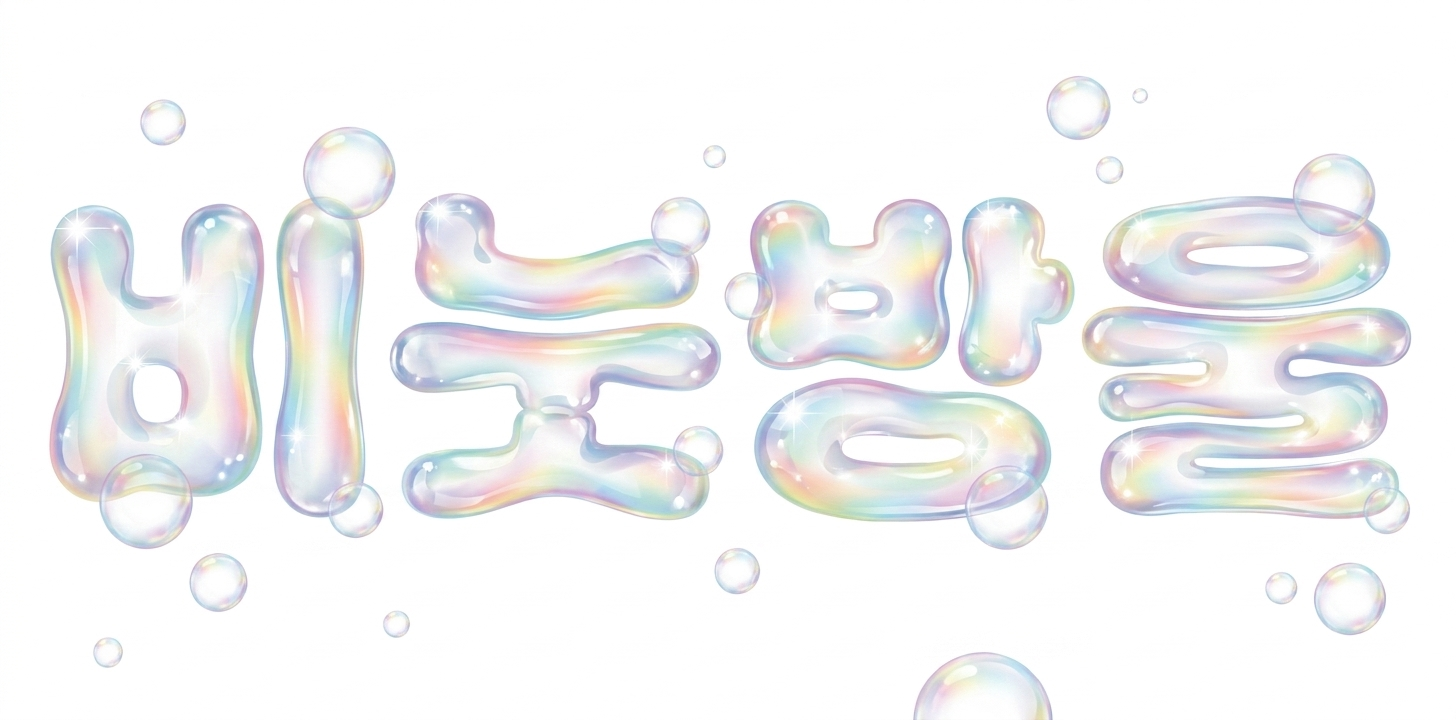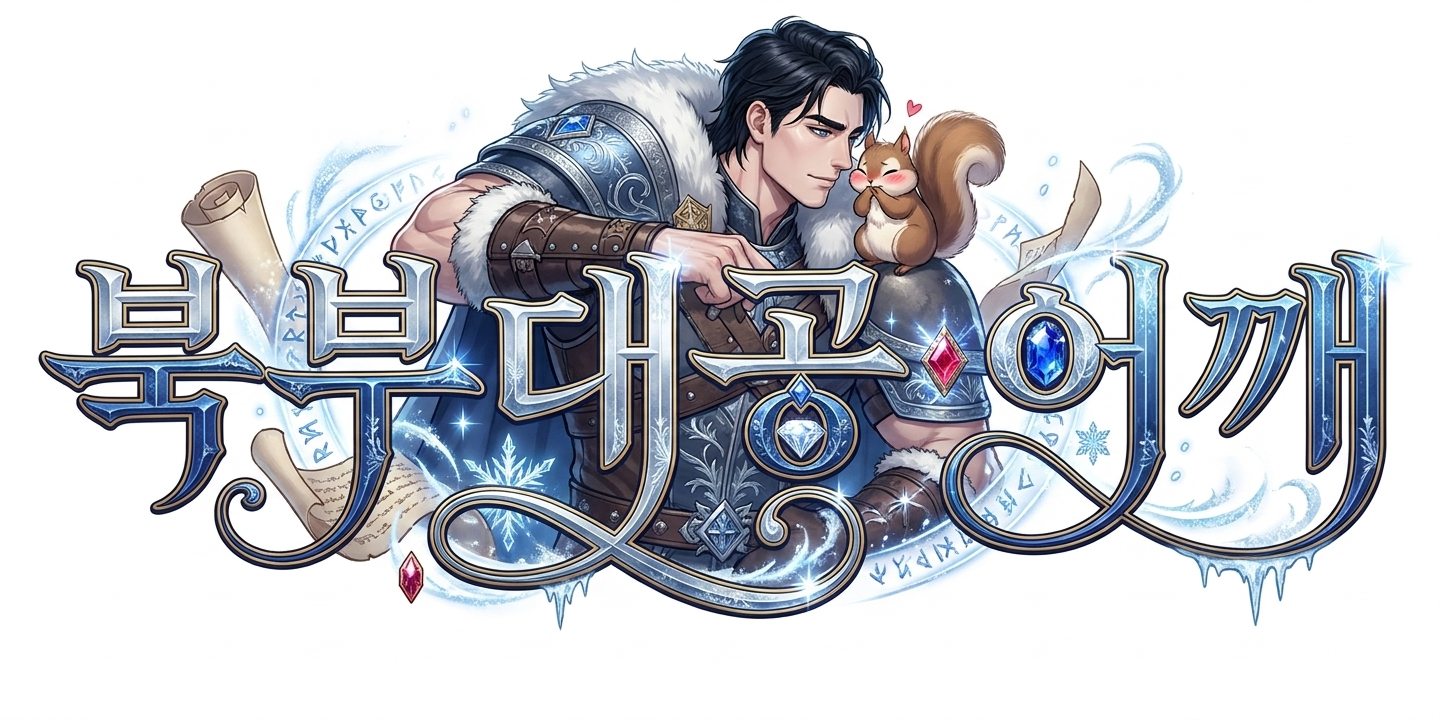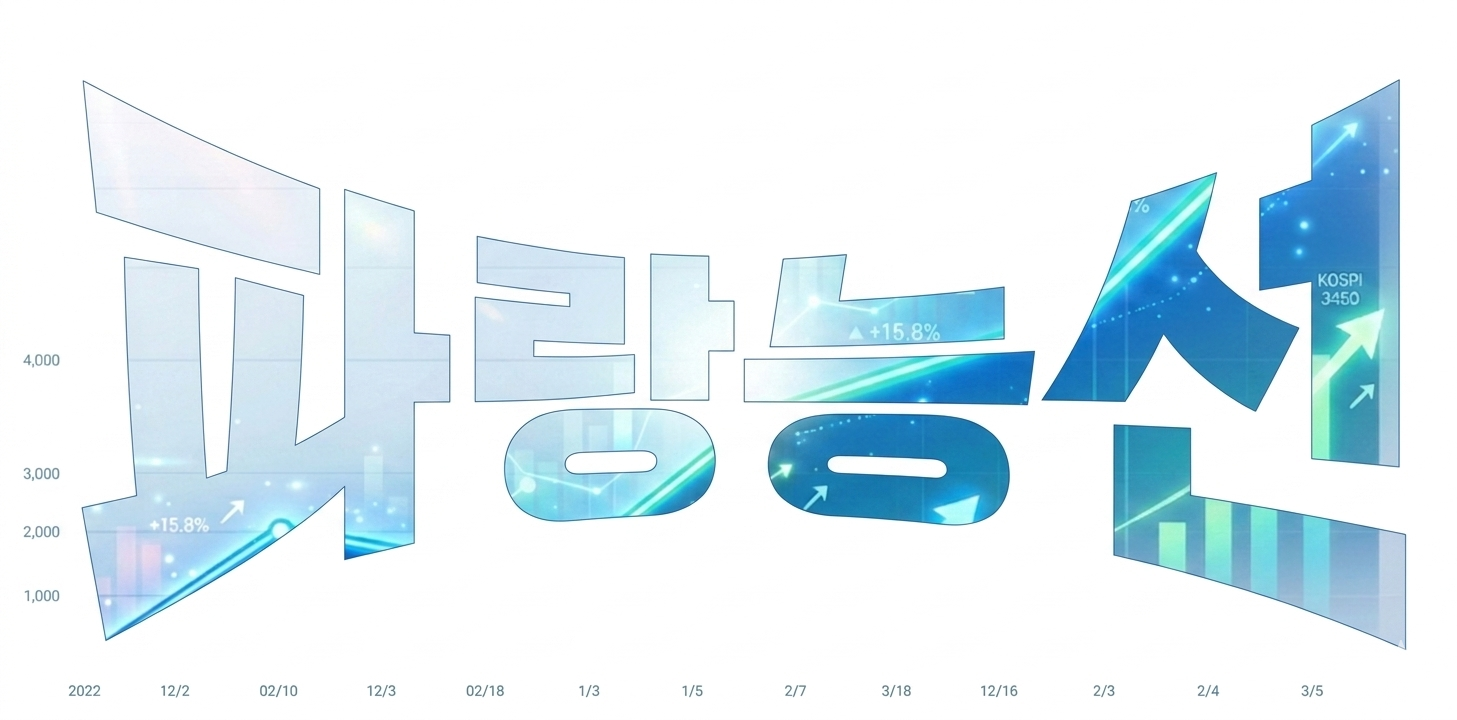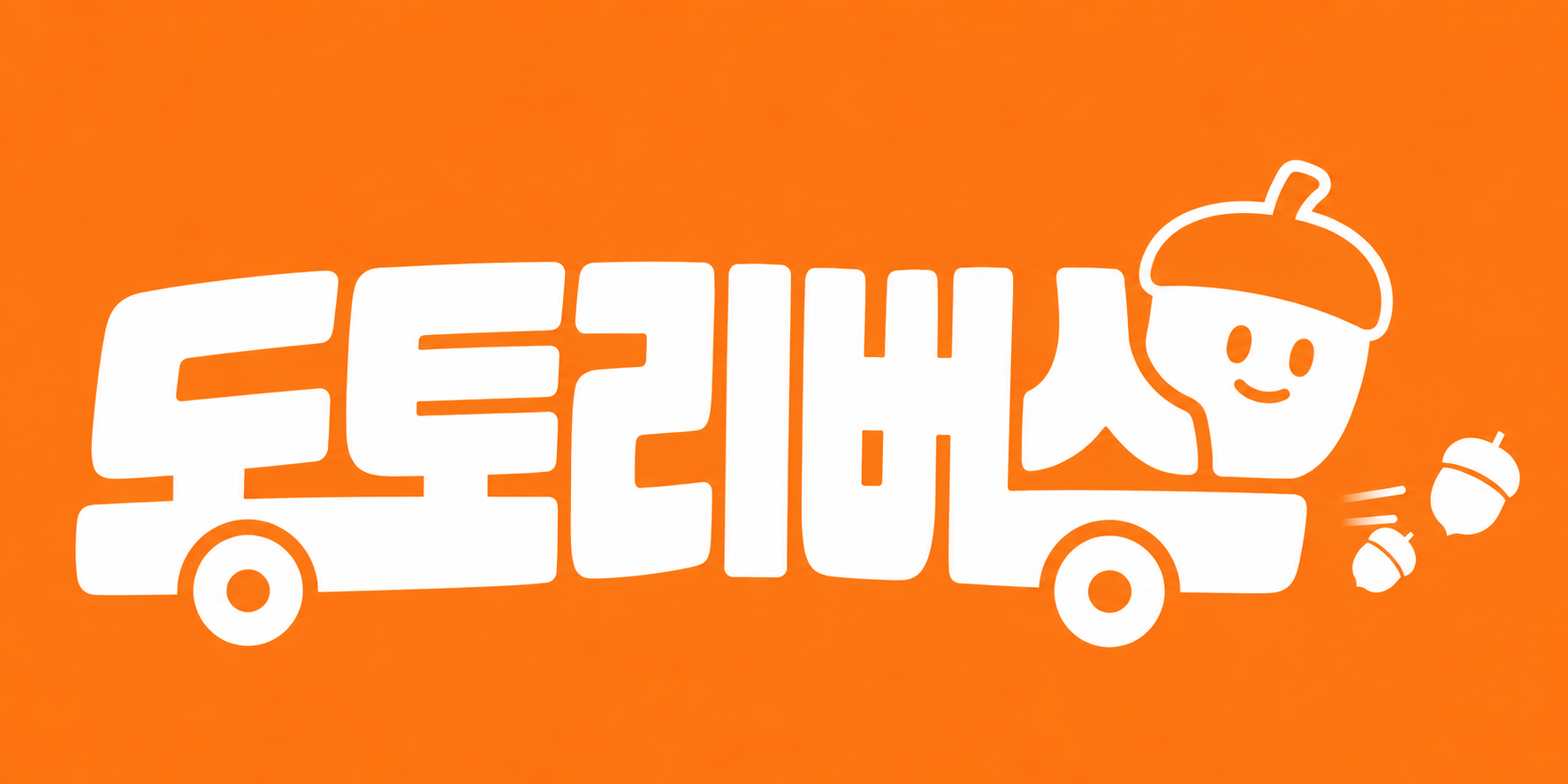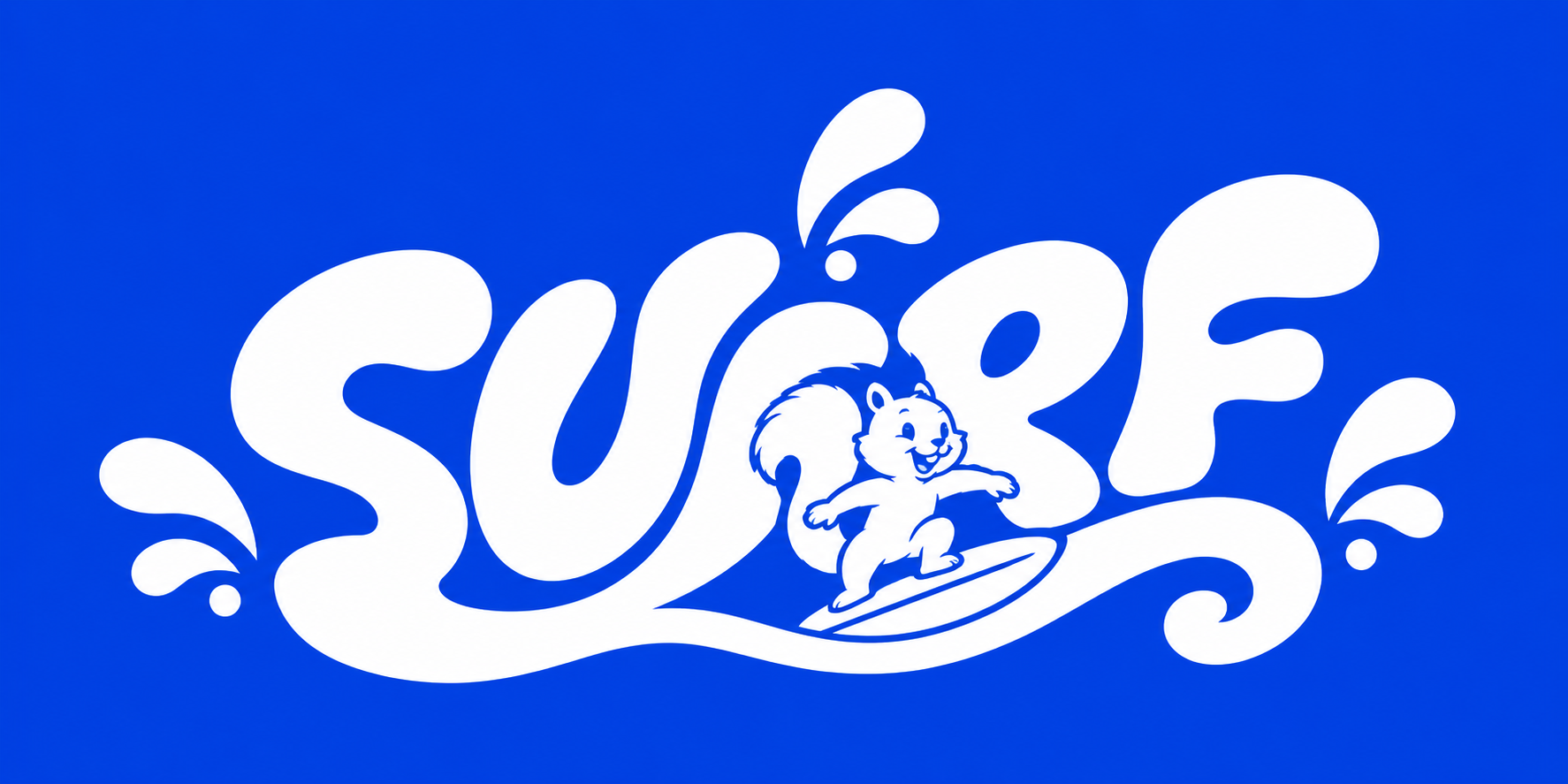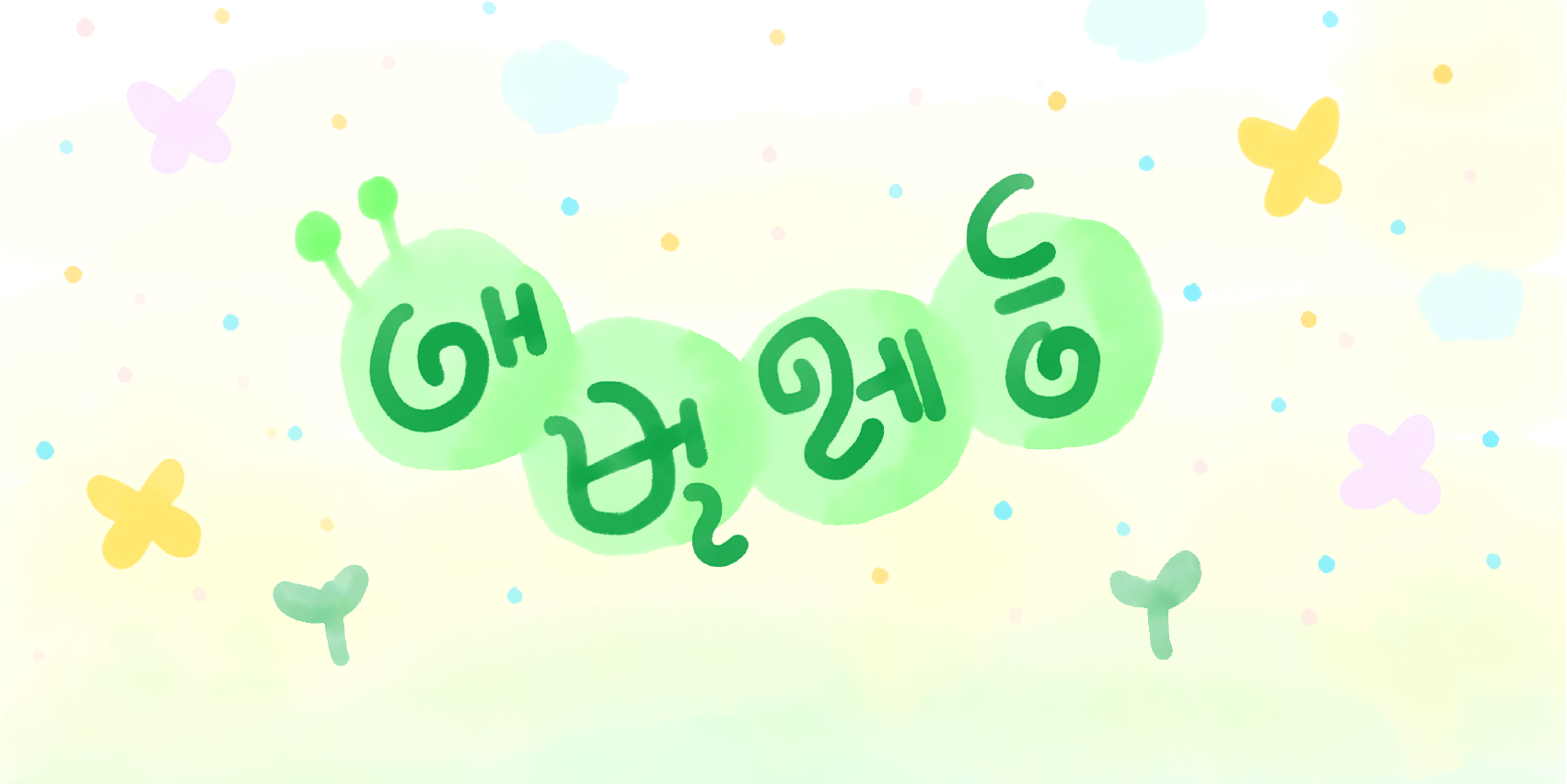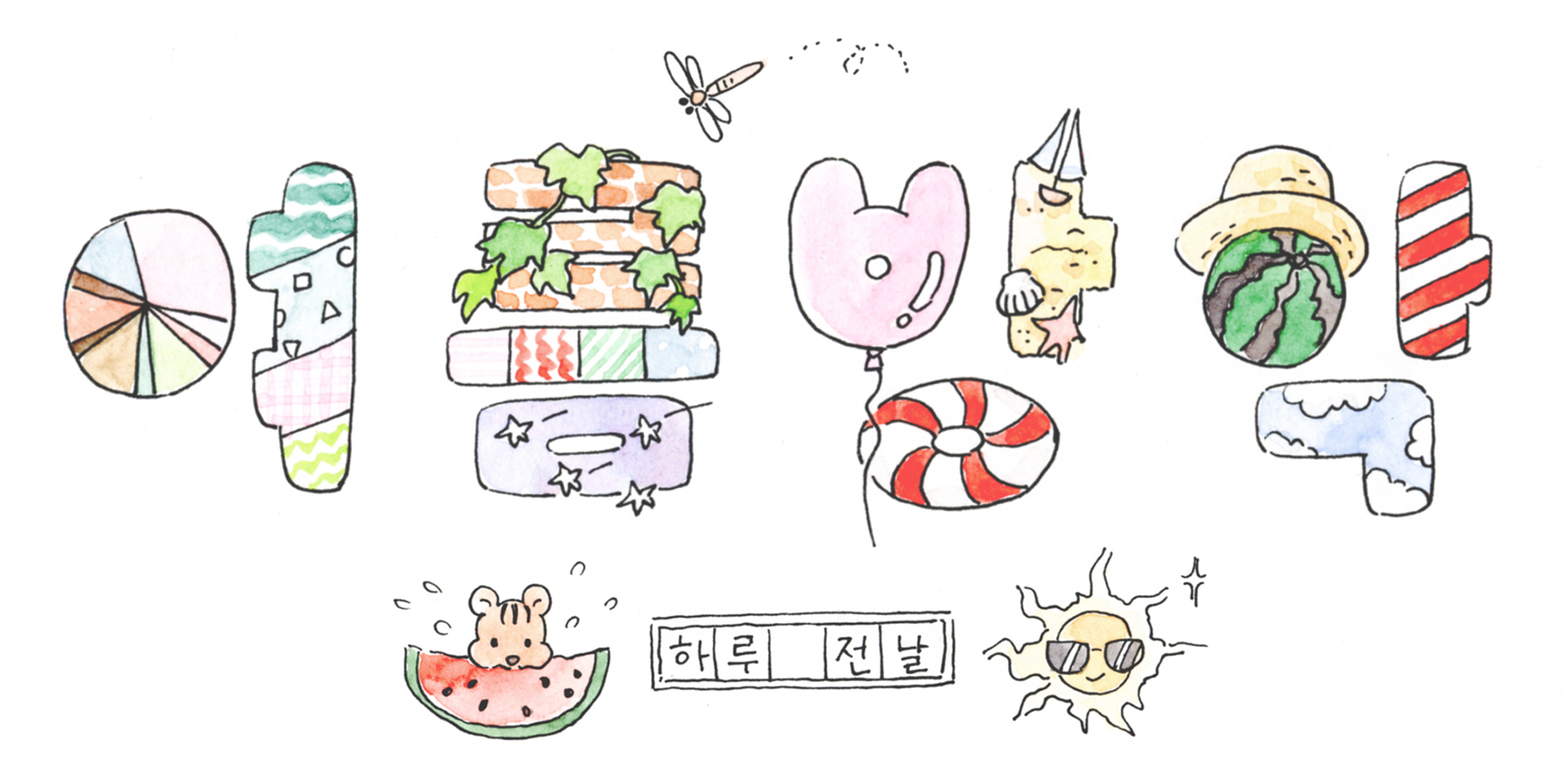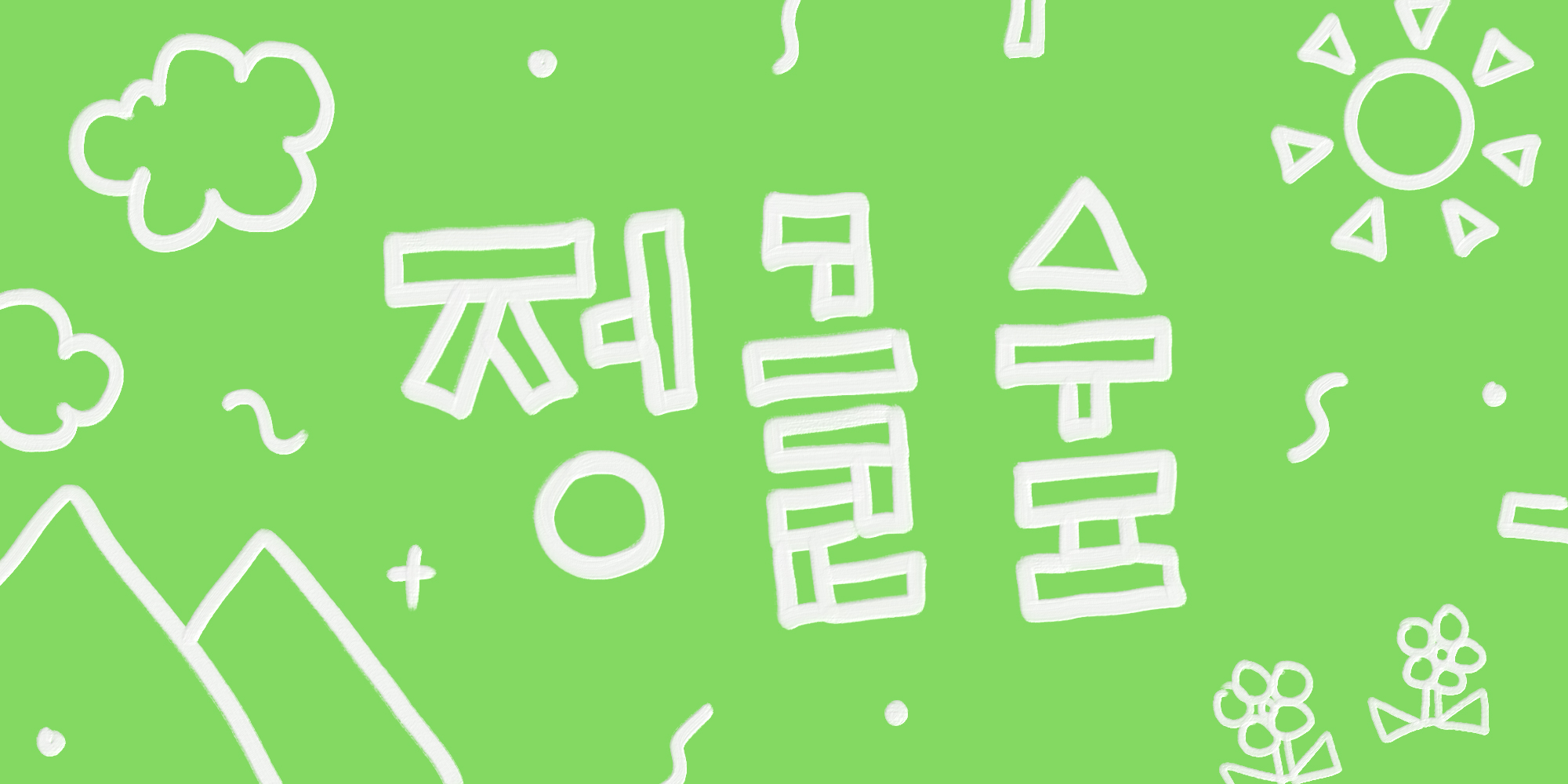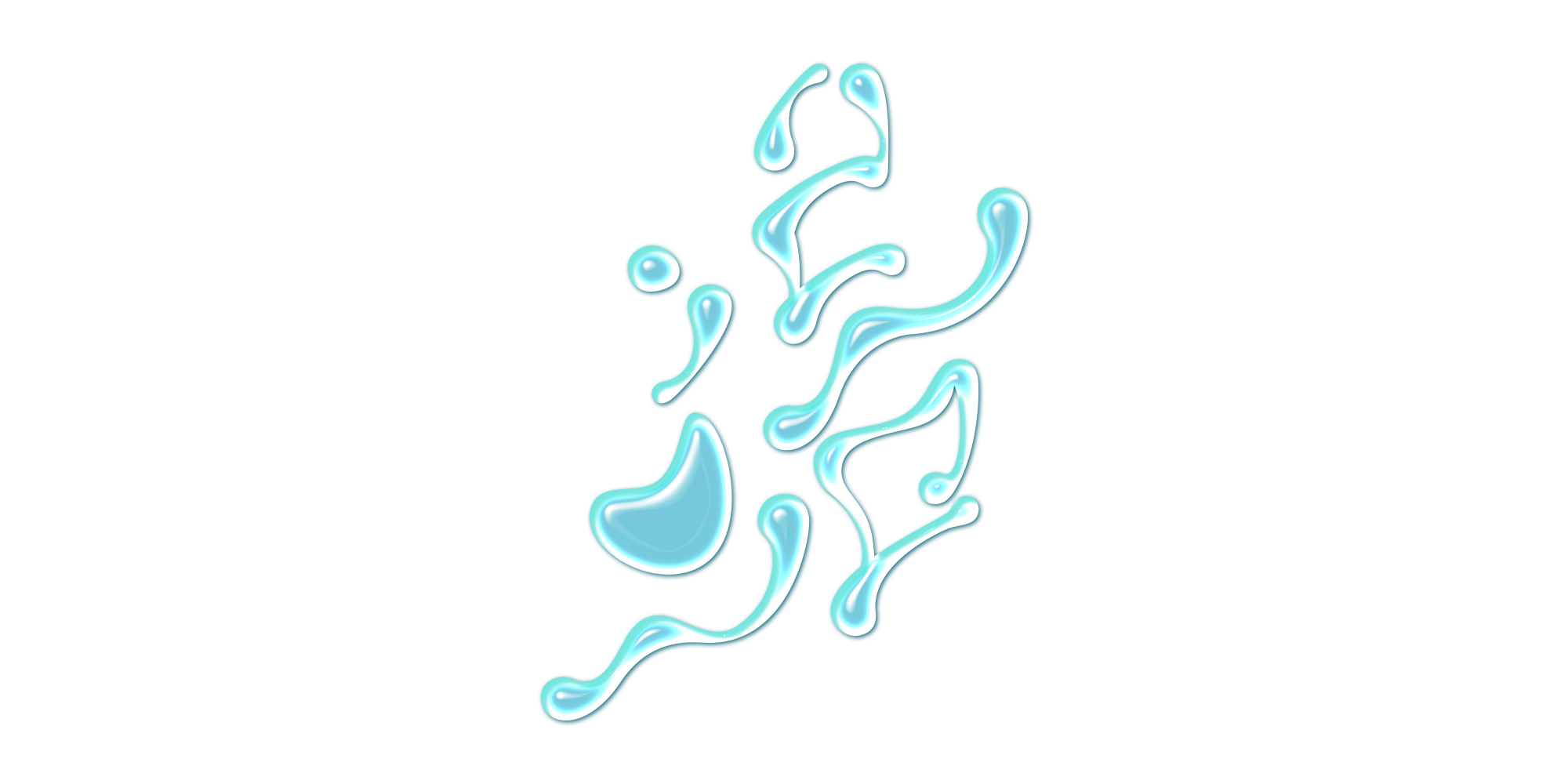
다람쥐와 함께 떠난 여정에 159개의 작품이 모였어요.
저마다의 상상으로 빈칸을 가득 채워준 덕분에, 다람쥐도 한참을 고민했답니다.
헌 쳇바퀴를 두고 갈아탄 새로운 자리는 어디였을까요?
1등 · 통합 1명
디지털 디자인
다람쥐 [ 흐름 ]에 타고파
runnynose
쳇바퀴 도는 일상 속에서도 어떤 흐름을 타게 되면 조금은 두근거리는, 열정으로 가득한 시간을 보내게 됩니다. 매일 같은 일상을 살아가는 다람쥐들이 쳇바퀴가 아닌, 기분 좋은 흐름에 올라타기를 바라봅니다.
2등 · 분야별 1명
디지털 디자인
다람쥐 [ SURF ]에 타고파
요니
여름이 다가오니 시원한 파도에 올라타고 싶어서 surf를 파도의 느낌을 살려 나타내보고자 함
손글씨
다람쥐 [ 정글숲 ]에 타고파
정글숲을 지나서가자
동그라미,세모,네모로 완성된 정글숲 글자!
폰트 놀이터
다람쥐 [ 북부대공어깨 ]에 타고파
김예진퇴사하라
헌 쳇바퀴보다는 조금 더 튼튼하고 안락하며
심심하지 않은 환경 같습니다.
3등 · 분야별 2명
디지털 디자인
다람쥐 [ 네잎클로버 ]에 타고파 꼬졔
행운의 다람쥐
디지털 디자인
다람쥐 [ 도토리버스 ]에 타고파 kay
맨날 뛰어다니기만 하던 다람쥐는, 가끔은 도토리버스에 타고파
손글씨
다람쥐 [ 애벌레등 ]에 타고파 애벌레귀여운손글씨수채화
수채화 스타일의 귀여운 애벌레 그림과 꼬물꼬물 귀여운 애벌레 글씨를 조합하여 꾸며보았습니다.
손글씨
다람쥐 [ 여름방학 하루 전날 ]에 타고파 이다람
조금 있으면 여름방학입니다. 학생이었던 때를 생각해 보면 방학했을 때보다 방학하기 하루 전날이 제일 좋았어요. 막상 방학 때는 즐기지 못했던 거 같아요. 기대로 가득했던 여름방학 하루 전날처럼 살고 싶다는 마음에 글자를 그렸습니다.
폰트 놀이터
다람쥐 [ 파랑능선 ]에 타고파 차희
다람쥐도 마음의 여유를 얻고싶은 소망이 있을것이라 상상해보았습니다.